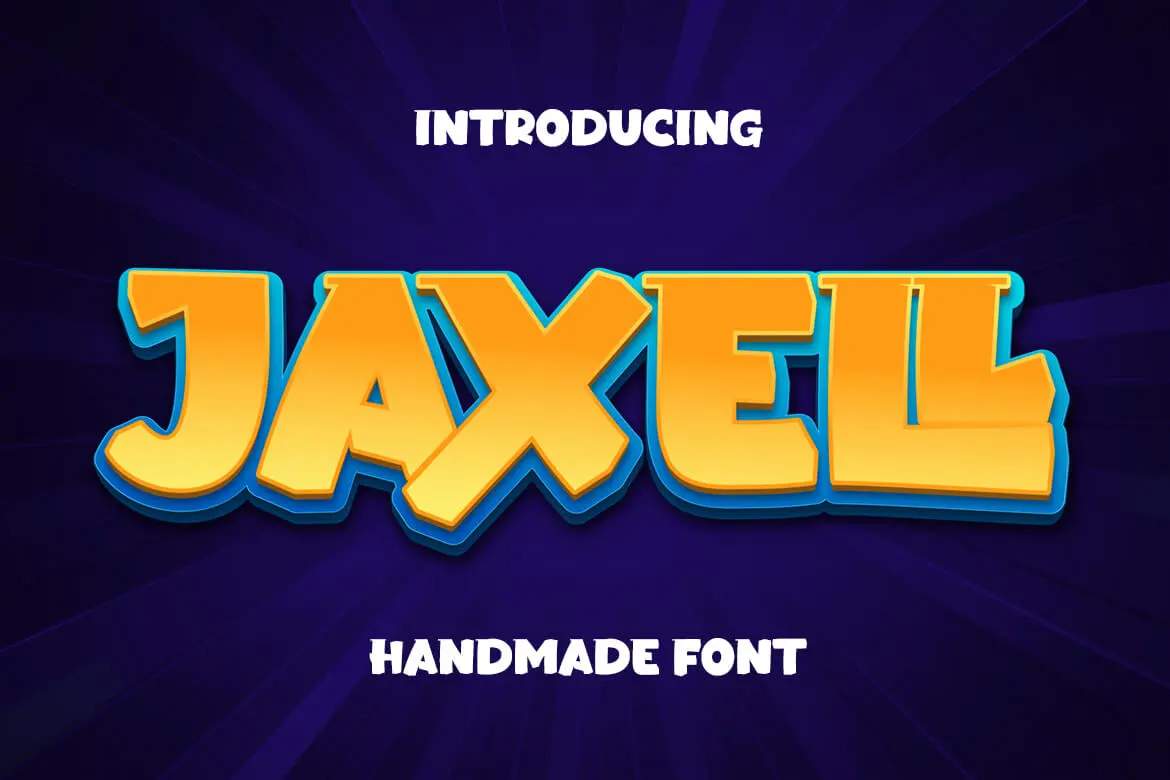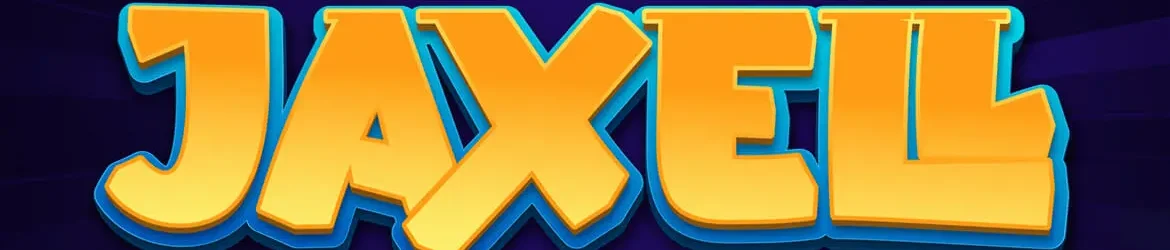
A fonte Jaxell Font é uma tipografia para destaque que traz características levemente fantásticas, com qualidades distintas e únicas. Ela se assemelha a um título de projeto enigmático ou divertido, fazendo dele um visual imediato e memorável. Além disso, Jaxell é igualmente encantadora quando usada em textos mais longos, como subtítulos ou descrições da página, proporcionando uma mistura perfeita de simplicidade e estilo. Essa fonte foi criada pela dupla letter, o que nos dá a garantia de qualidade e originalidade. Com seu design dinâmico e personalizado, Jaxell é ideal para estilos mais elaborados e criativos em suas aplicações. Seja você um designer gráfico ou um web developer, Jaxell é uma escolha perfeita para dar um toque único a seus projetos digitais. Sem dúvida alguma, ela certamente encaixa-se na categoria de fontes de display, dando um brilho especial aos textos em sua página.